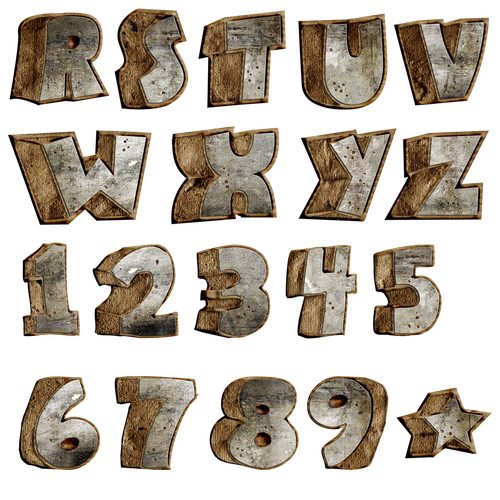
Неважно какой у вас личный стиль, но вам обязательно необходимо иметь широкий выбор шрифтов в вашей библиотеке дизайна. Это поможет вам всегда иметь под рукой шрифт, над которым вы работаете, независимо от типа проекта.
В большинстве случаев лучшим выбором будет традиционный выбор. Шрифты с засечками, без засечек, сценарии или декоративные шрифты прекрасно дополнят ваш дизайн и помогут передать правильный тон и сообщение. Но иногда вам нужно будет использовать что-то более необычное, а не то к чему вы привыкли.
В таких случаях короткие и трехмерные шрифты могут быть именно тем, что вам нужно. Эти шрифты идеально подходят для брендинга проектов для брендов, которые хотят выделяться и восприниматься как оригинальные и смелые. Короткие и трехмерные шрифты также являются отличным выбором для дизайна футболок, плакатов, рекламных щитов, рекламных материалов и любых других типов дизайнерских проектов.
Помните, что эти типы шрифтов могут доминировать в дизайне, поэтому лучше использовать их вместе с более простым шрифтом и, конечно же, избегать их использования в длинных предложениях или абзацах.
Учитывая количество доступных в сети шрифтов, поиск лучшего объемного или трехмерного шрифта для вашего проекта может занять много времени, вместо этого можно продолжать работу над проектом. Вот почему мы собрали лучшие объемные и трехмерные шрифты со всего Интернета для вас.